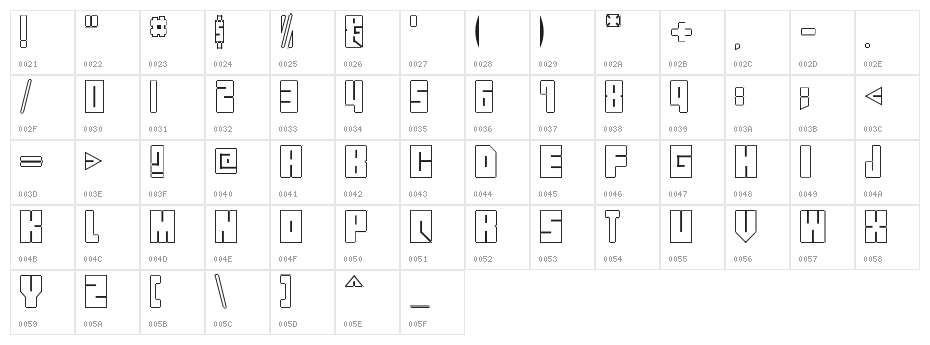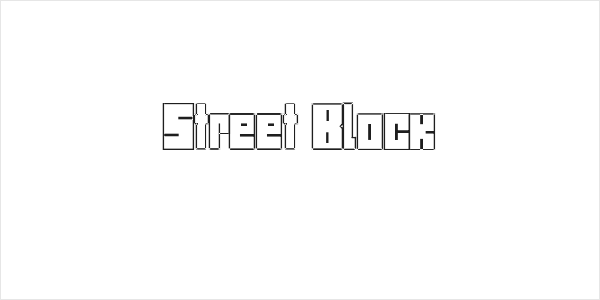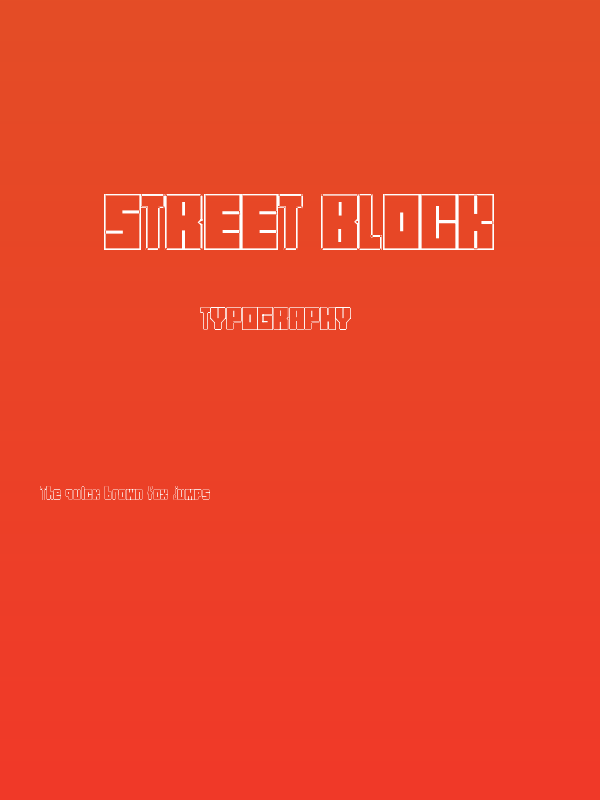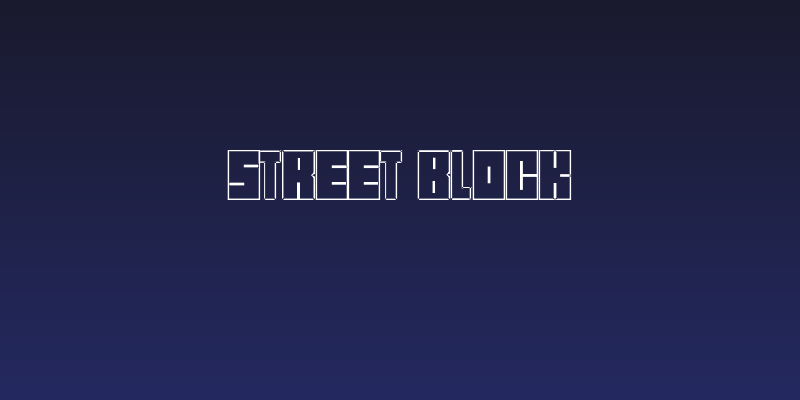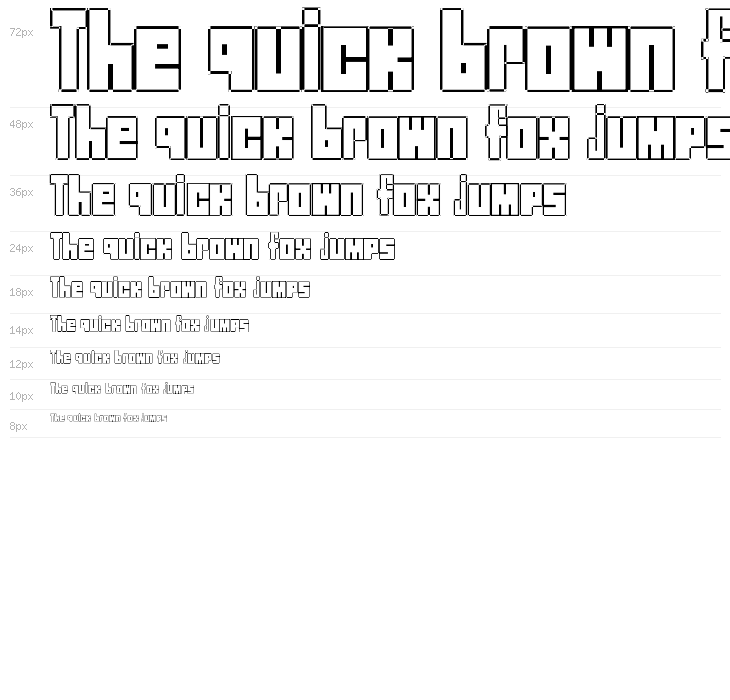
Street Block Font
| Vorgeschlagene Projekte | Ideal for urban-themed designs, streetwear branding, posters, and digital artwork that requires a modern and edgy look. |